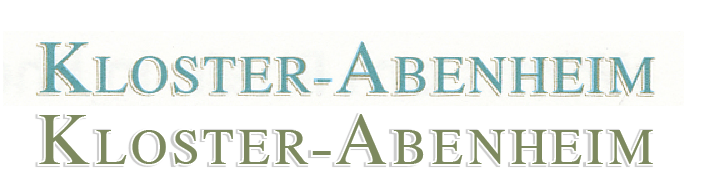
ist gesucht!
bekam bereits den tipp, dass diese
Castellar
Colonna
Imprint
Niagara Engraved
in die richtung gehen.
allerdings brauche ich exakt diesen font.
Ich würde mal sagen dass das eine Nimbus Roman ist und der "Schatten" von Hand hinzugefügt wurde.
die nimbus wurde mir auch schon vorgeschlagen.
andererseits wurde mir auch gesagt, dass es den font jawohl gibt und ich da bloß nichts mit schatten nachbauen soll.
das sieht aus wie ein weicher schatten. der ist sicher aus keinem font, sondern zb im photoshop gabastelt (noch dazu mit licht von rechts oben. sonst kommt licht fast immer von links oben – zumindest bei den meisten grafikern) :oops:
Hab einfach mal die Times über deine Grafik gelegt (cyan)
Wer auf falsche Kapitälchen setzt, macht sich vielleicht auch nicht sonderlich Mühe bei der Schriftwahl. Wäre jetzt so mein abstrakter Gedankenweg.
Bis auf kleinste Details :?
den gedanken hatte ich auch schon, aber trotzdem auch die hoffnung, dass das ein font ist und kein nachträglich hinzugefügter schatten.
das bau ich jedenfalls jetzt nicht nach. imprint shadow ist drin, mal gucken, obs ankommt.
Das ist bestimmt was Händisches, allein schon wegen der Zweifarbigkeit von Schrift und Schatten. Sowas kriegt man zwar auch als "Set", aber dann hätte der Font gewiss anständige Kapitälchen. Bei der Imprint ist es halt ein Binnenschatten ...
:tuschel: Das Ursprungsbild ist doch aber einfarbig …
Bertel: Kannst Du etwa irgendwie Times New Roman und Nimbus unterscheiden? :o
Ja, kann ich: Times schreibt sich mit einem „T“, Nimbus mit einem „N“ … :mrgreen:
Nee, ganz ehrlich, ich hab das nur schnell durch wtf gejagt und da kam Nimbus raus, also hab ich das mal gepostet :cheer: